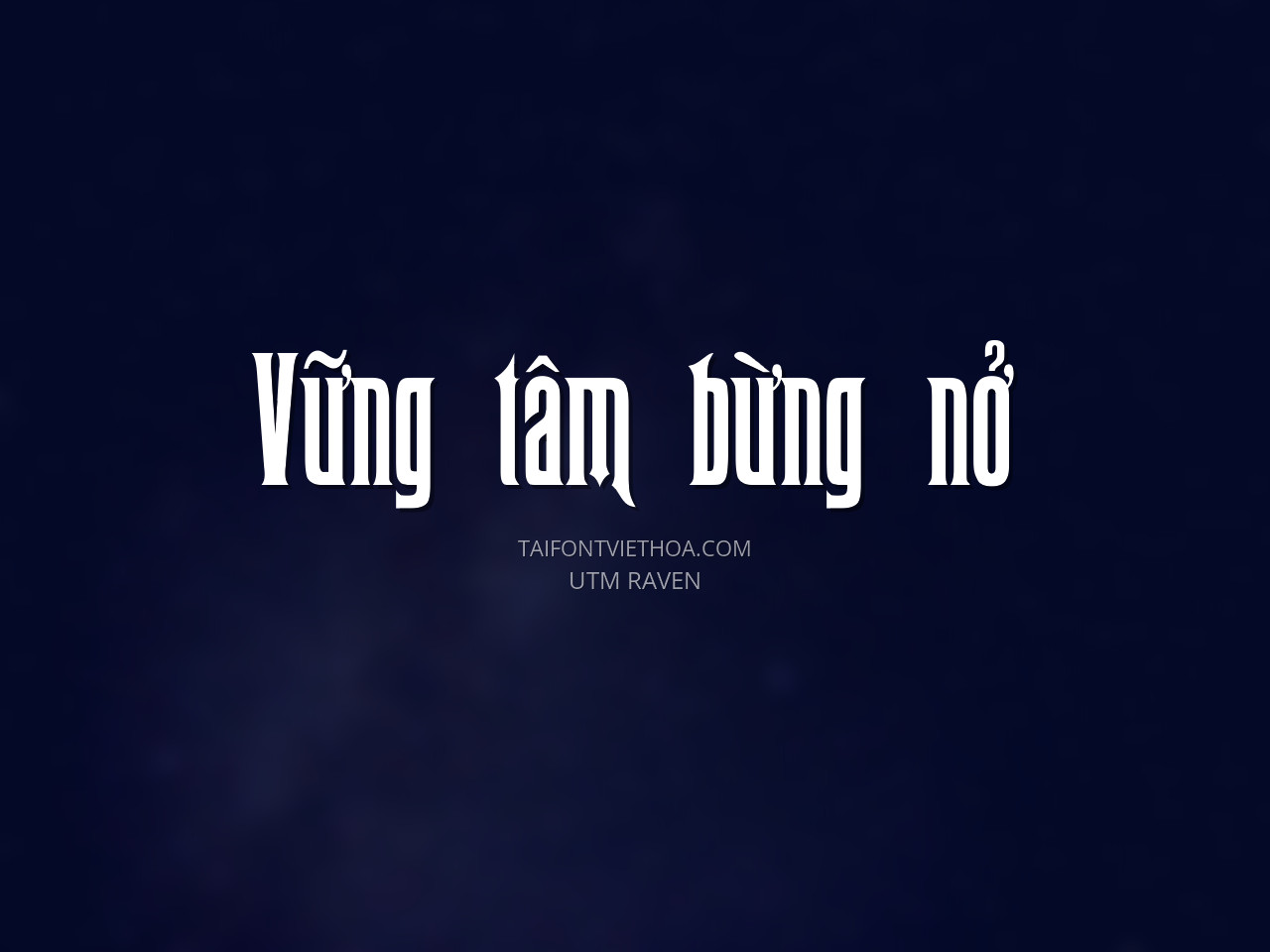
Font việt hóa UTM Raven
Giới thiệu về font UTM Raven
UTM Raven là phiên bản Việt hóa của font Raven – một kiểu chữ serif mạnh mẽ và cá tính, mang phong cách hiện đại pha chút cổ điển, thích hợp cho các dự án thiết kế cần sự nổi bật và chuyên nghiệp. Font gốc nổi bật với các nét chữ có chân sắc nét, cấu trúc cân đối và độ tương phản rõ ràng, rất phù hợp cho các ấn phẩm branding, in ấn và quảng cáo cao cấp. Phiên bản Việt hóa đã được hoàn thiện để hỗ trợ đầy đủ tiếng Việt cùng hơn 150 ngôn ngữ khác, mở rộng khả năng ứng dụng trong nhiều lĩnh vực thiết kế đa dạng.
Font UTM Raven được taifontviethoa.com sưu tầm và lựa chọn kỹ càng nhằm phục vụ cộng đồng thiết kế Việt Nam. Phiên bản Việt hóa giữ nguyên nét cá tính và sang trọng của bản gốc, đồng thời tối ưu khả năng hiển thị tiếng Việt, rất phù hợp cho các dự án branding, in ấn và truyền thông đa phương tiện.
Đặc điểm thiết kế và ứng dụng của UTM Raven
UTM Raven sở hữu cấu trúc serif với các nét chân chữ sắc nét, cân đối và thiết kế hài hòa. Font có độ dày vừa phải, tạo cảm giác mạnh mẽ, dễ đọc và chuyên nghiệp. Font phù hợp cho cả tiêu đề và nội dung chi tiết, mang lại sự sang trọng và ấn tượng cho các sản phẩm thiết kế.
Font thích hợp sử dụng trong thiết kế sách, tạp chí, nhận diện thương hiệu, quảng cáo, bao bì sản phẩm sang trọng và các dự án truyền thông đa phương tiện. Các ngành nghề phù hợp gồm: xuất bản, thời trang, tổ chức sự kiện, nghệ thuật, giáo dục và thiết kế nội thất.